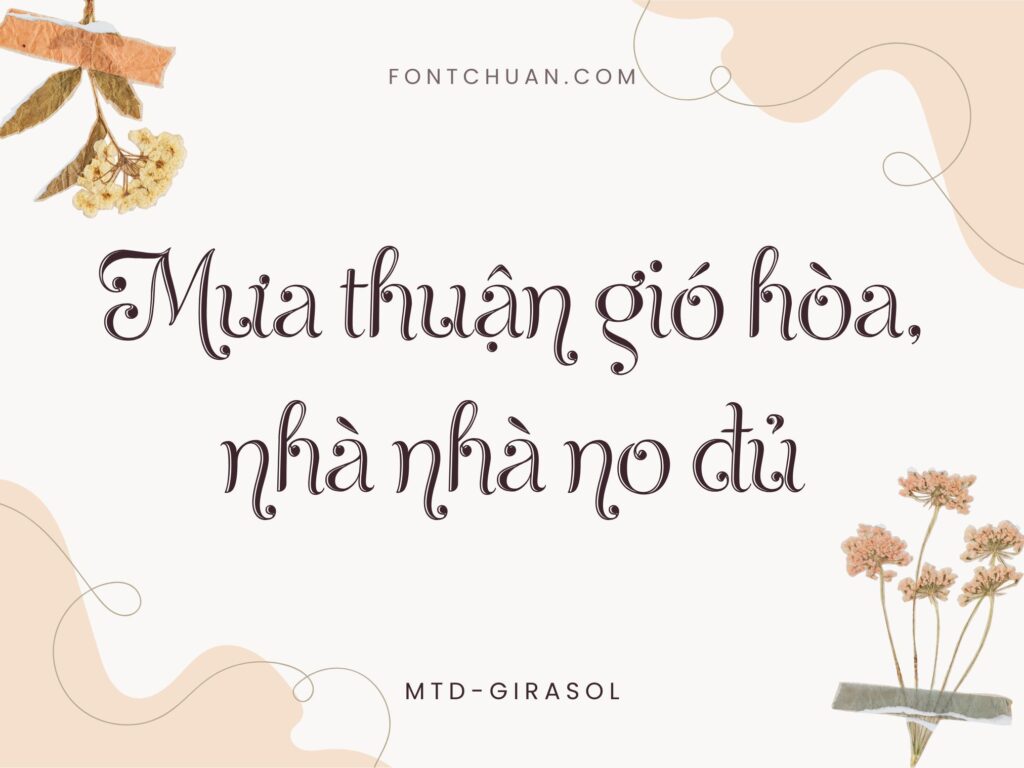
Font MTD Girasol Việt Hóa
Font MTD Girasol là một kiểu chữ serif hiển thị với thiết kế độc đáo, mang đến vẻ đẹp cổ điển và sang trọng. Được thiết kế bởi Liam Spradlin và Việt hóa bởi Mộc Hạ, font này hỗ trợ đầy đủ tiếng Việt cùng hơn 90 ngôn ngữ khác, mở rộng khả năng ứng dụng trong các thiết kế đa ngôn ngữ. Đây là một trong những phông chữ được cộng đồng thiết kế đánh giá cao và sử dụng trong nhiều dự án sáng tạo, đáp ứng nhu cầu đa dạng của người dùng.
MTD Girasol nổi bật với các đường nét thanh lịch và tinh tế, tạo cảm giác chuyên nghiệp và đẳng cấp. Font rất phù hợp cho các thiết kế logo, tiêu đề, bao bì sản phẩm, thiệp mời và các ấn phẩm đòi hỏi sự sang trọng và nghệ thuật. Các ngành nghề phù hợp bao gồm quảng cáo, giáo dục, công nghệ, thiệp cưới và ảnh cưới. Font này cũng lý tưởng cho các sự kiện như Tết, Giáng sinh, Valentine và các lễ hội khác.